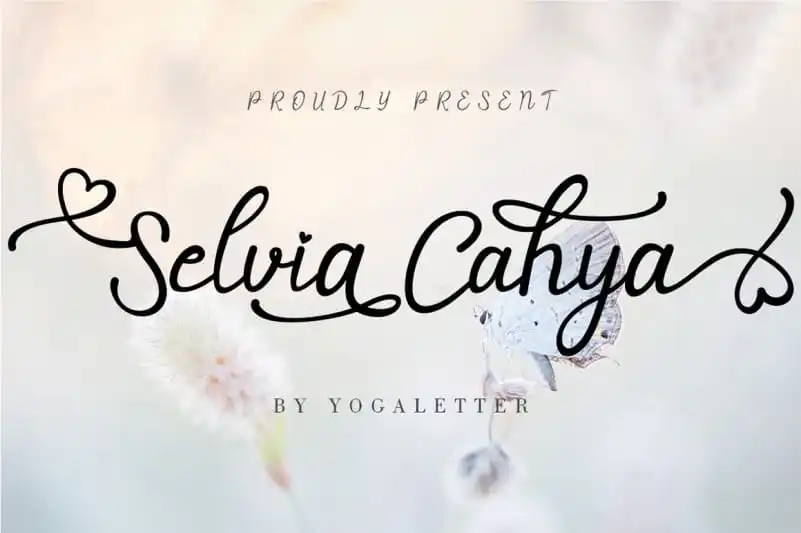
A Selvia Cahya Calligraphy Font é uma escolha elegante para projetos que exigem um toque delicado e moderno. Com seu traçado fluido e suave, esta fonte script pode ser utilizada em uma ampla variedade de projetos, como criar cartões de casamento ou aniversário encantadores para crianças, arte impactante, postagens interessantes nas redes sociais e cartas de cumprimentos hilares. Suas linhas fluidas e harmoniosas são perfeitas para dar um toque sofisticado a qualquer projeto, seja ele um convite personalizado para casamento ou uma publicação em redes sociais divertida. Selvia Cahya é especialmente adequada para designers que desejam adicionar um toque de elegância ao seu trabalho. Suas linhas finas e equilibradas permitem uma tipografia precisa, enquanto sua composição suave evoca o charme e a delicadeza do estilo calligrafia moderna. A fonte é perfeitamente adaptada para criação de layouts variados que vão desde cartões de cumprimento até trabalhos publicitários, tudo mantendo uma estética sofisticada e atemporal.